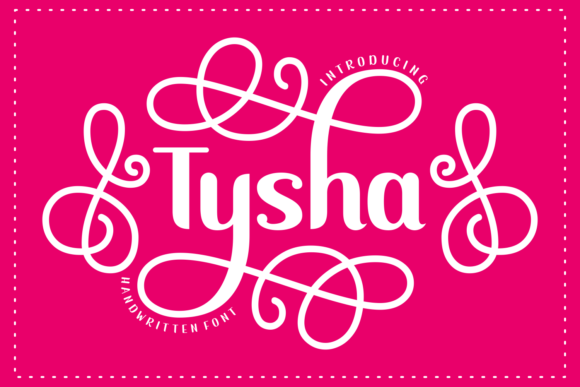
Creativefabrica Tysha Font 2021
[Creativefabrica] Tysha Font (2021)
Tysha - это классный, детальный и причудливый шрифт.
Смело добавляйте его в свои любимые творения и позвольте себе поразиться полученному результату.